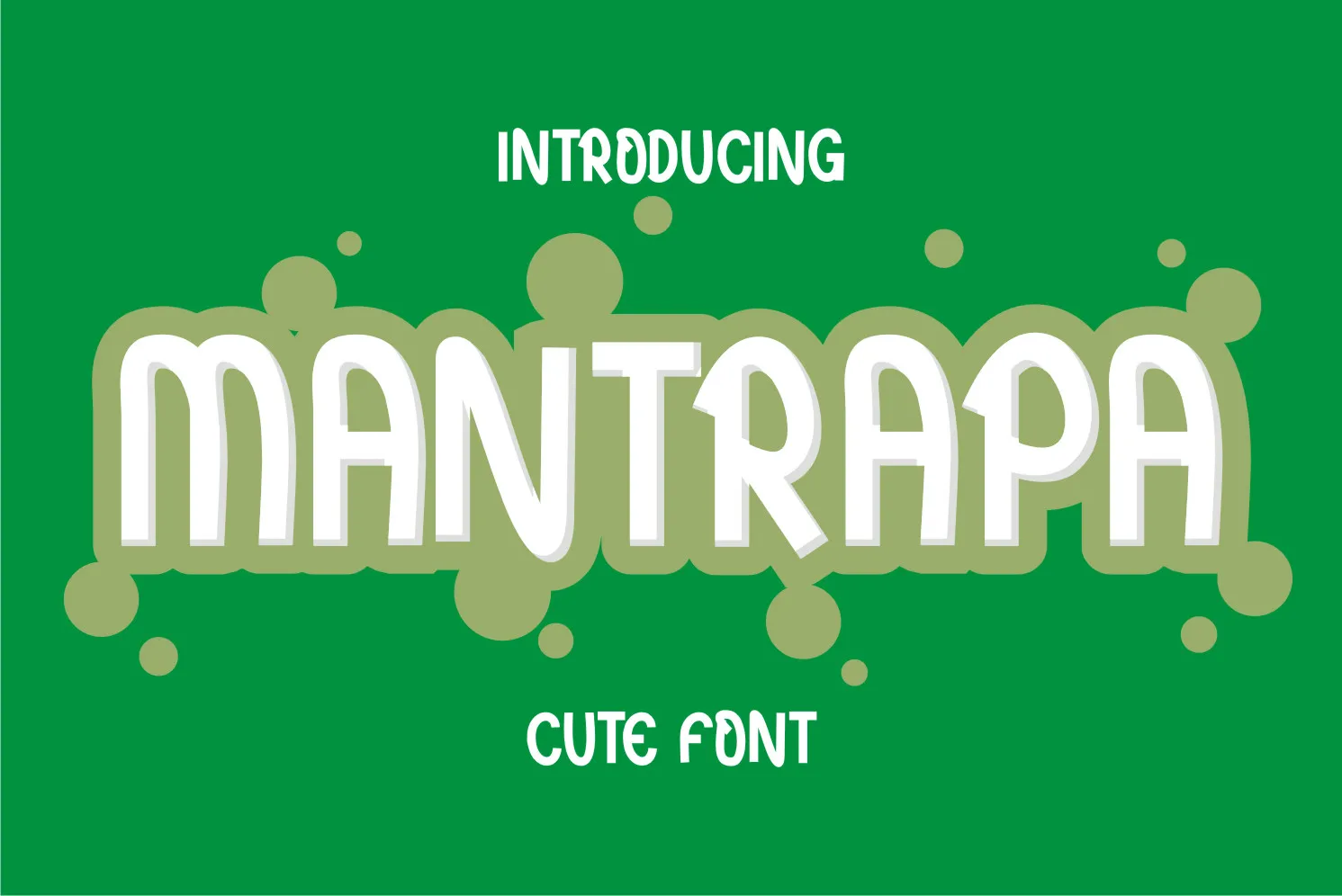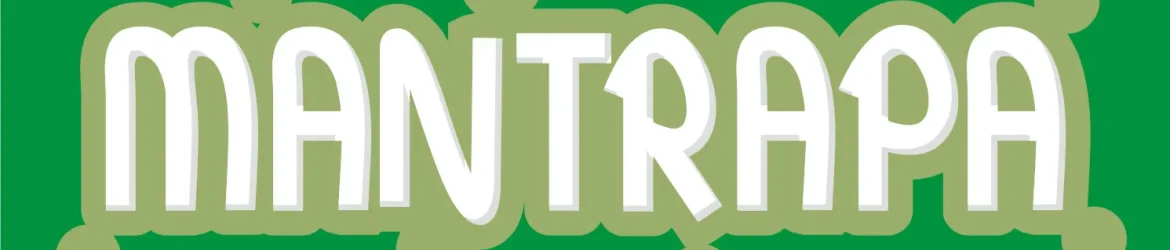
Esta é uma bela fonte de exibição ‘Mantrapa Font’, projetada pela letterfiastudio. Ela se destaca por ser cool e simples, com um estilo alegre e moderno que torna-a perfeita para enriquecer qualquer criação gráfica linda que necessite de um toque amigável e informal. Seja para rótulos, logotipos ou materiais de marketing pessoal, ela trará uma atmosfera descontraída e atual aos seus projetos visuais. Engane-se com a simplicidade dessa fonte; ela carrega consigo elementos que o tornam um recurso versátil para qualquer projeto gráfico atemporal e sofisticado. Descubra por si mesmo os benefícios de usar ‘Mantrapa Font’ em suas criações, ele vai transformar seu design em uma experiência visual agradável.